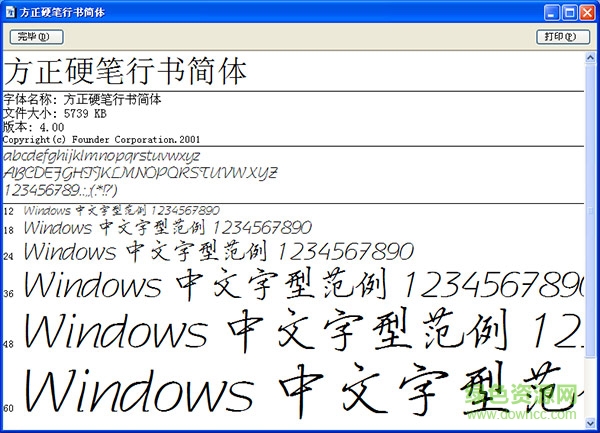
fzybxsjw gb1 0是什么字體?fzybxsjw gb1 0字體就是方正硬筆行書(shū)簡(jiǎn)體,結(jié)構(gòu)嚴(yán)謹(jǐn)字形大方,粗細(xì)變化得宜,筆鋒富有力度,常常應(yīng)用于各類(lèi)創(chuàng)意設(shè)計(jì)或文字藝術(shù)設(shè)計(jì)方面,需要的朋友歡迎在綠色資源網(wǎng)下載!
行書(shū)是介于楷、草間的一種書(shū)體。寫(xiě)得比較放縱流動(dòng),近于草書(shū)的稱行草;寫(xiě)得比較端正平穩(wěn),近于楷書(shū)的稱行楷。
行書(shū)書(shū)寫(xiě)應(yīng)輕松、活潑、迅捷,掌握好疾與遲、動(dòng)與靜的結(jié)合。墨色安排上應(yīng)首字為濃,末字為枯。線條長(zhǎng)細(xì)短粗,輕重適宜,濃淡相間。和草書(shū)差不多,但沒(méi)那么草。
fzybxsjw gb1 0字體筆畫(huà)一氣呵成,線條連綿頗具氣勢(shì),清晰韻致,整體效果出色,實(shí)用性和藝術(shù)性兼?zhèn)洌?/p>